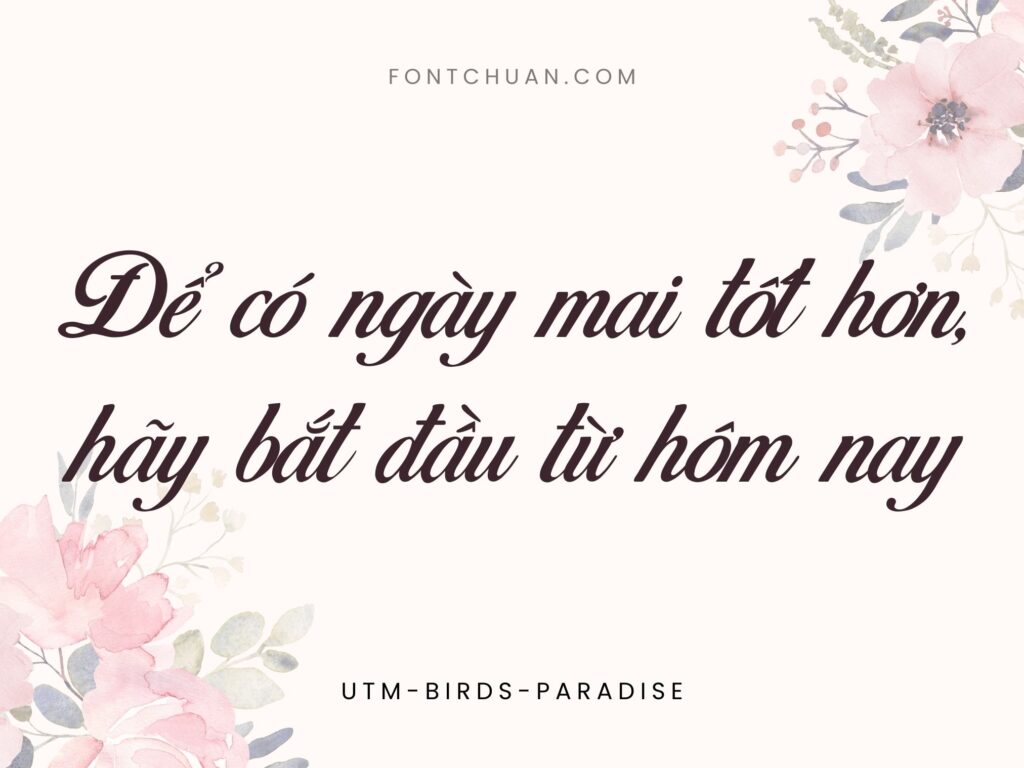
Font UTM Birds Paradise Việt Hóa
UTM Birds Paradise là phiên bản Việt hóa của font chữ Birds of Paradise, một kiểu Font Script được thiết kế bởi Guilhem Greco vào năm 2014. Font này nổi bật với các đường nét mềm mại, uyển chuyển và phong cách viết tay thanh lịch, tạo cảm giác lãng mạn và tinh tế. Phiên bản Việt hóa đã được thực hiện, hỗ trợ đầy đủ tiếng Việt cùng hơn 100 ngôn ngữ khác. Đây là một trong những font được cộng đồng thiết kế sưu tầm và chọn lọc nhằm đáp ứng nhu cầu đa dạng trong thiết kế.
UTM Birds Paradise có cấu trúc chữ với các nét nối liền mạch và độ nghiêng nhẹ, tạo nên sự mềm mại và dễ đọc. Font này phù hợp cho các ứng dụng như thiết kế thiệp mời, tiêu đề, logo và các ấn phẩm in ấn yêu cầu sự trang nhã và nghệ thuật. Các ngành nghề như quảng cáo, giáo dục, công nghệ và bất động sản có thể tận dụng UTM Birds Paradise để tạo điểm nhấn độc đáo trong thiết kế.